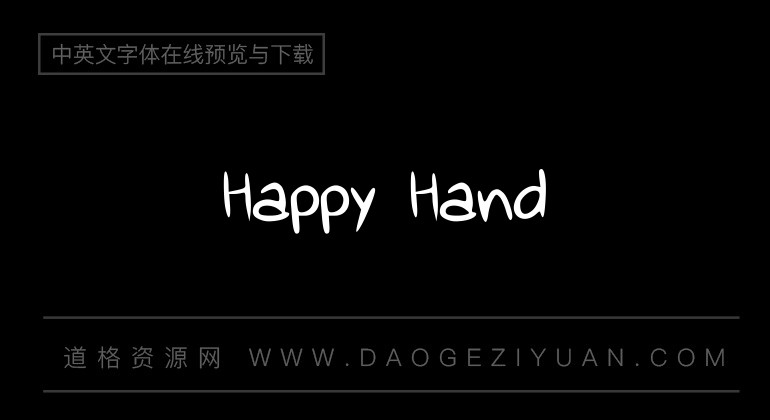
Happy Hand 是一种手写风格的字体,其特点是多样化的笔画和明亮的颜色,让人感到轻松和愉悦。它的字母形态非常流畅和自然,就像是一个人在用手写字体书写一样。这种字体非常适合用于卡片、海报、广告、书籍和其他文化产品的设计中。 此外,Happy Hand 还有多种风格和变体,比如粗体、斜体、下划线等等。这些变体可以让设计师更好地控制文本的排版和视觉效果,而且整体风格非常统一,让设计作品更加美观和流畅。内容介绍
Happy Hand是一款非常不错的手写艺术字体,具有很好的视觉感,适合于文化类的宣传设计、商业类品牌的广告和产品包装设计以及个性化文字排版等较多场景。